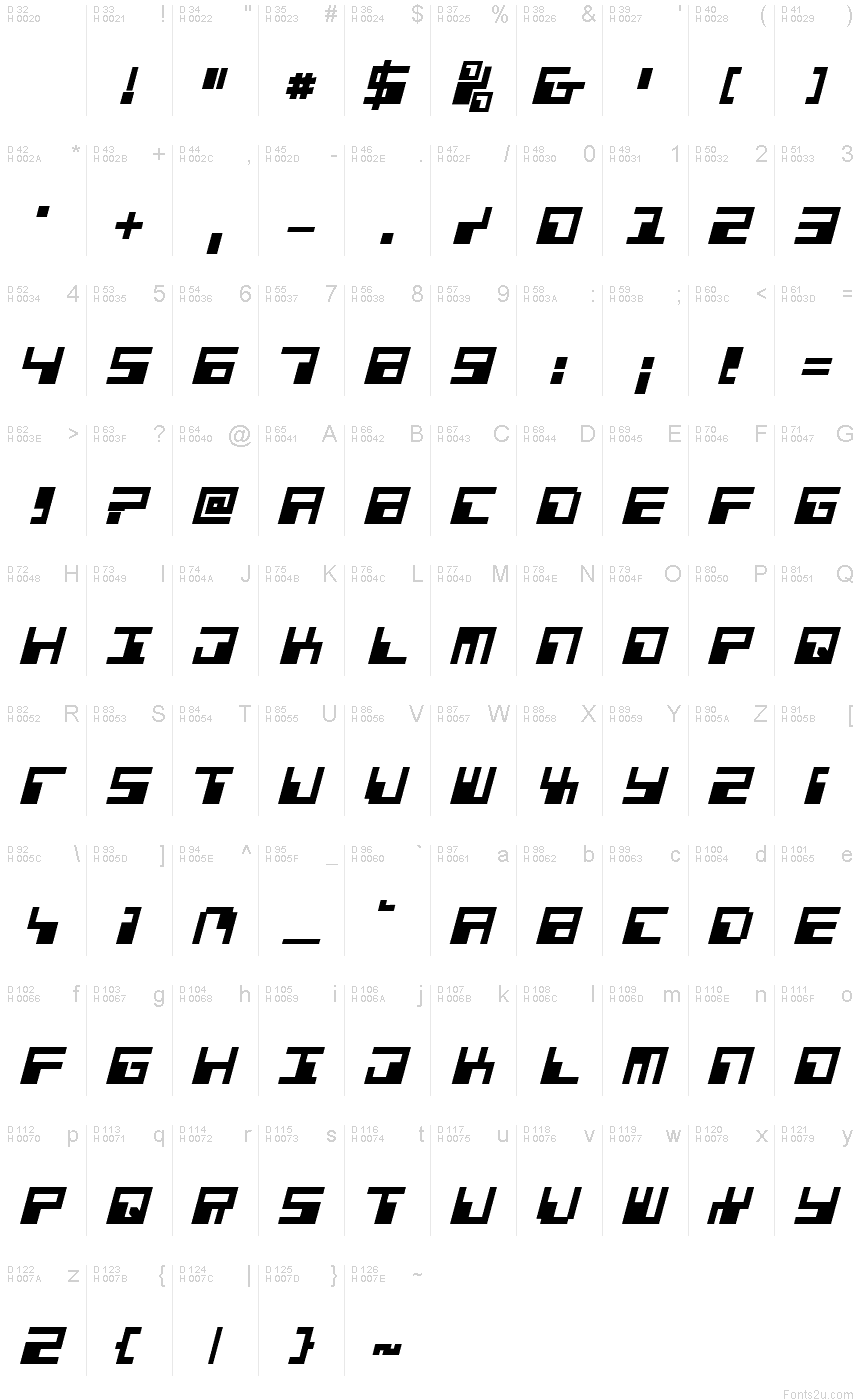
Phaser Bank Bold Italic, darmowy, futurystyczny krój techno w wielkich literach od Iconian Fonts, nawiązuje do stylistyki sprzętu arcade dzięki wyraźnemu pochyleniu do przodu. Szerokie, kwadratowe formy są przecięte ostrymi ukośnymi cięciami, a wąskie przerwy i powtarzające się poziome paski nadają literom szybki, techniczny rytm.
Ta kanciasta dynamika tworzy natychmiastowe wrażenie prędkości w identyfikacjach e-sportowych i tytułach gier wyścigowych, świetnie sprawdzając się również na plakatach sci-fi i grafikach związanych z muzyką elektroniczną. Użyj tego darmowego fontu do opakowań technologicznych lub oznaczeń imprezowych, gdy kompozycja wymaga liter, które sprawiają wrażenie maszynowych, pilnych i osadzonych w estetyce wczesnego cyfrowego futuryzmu.